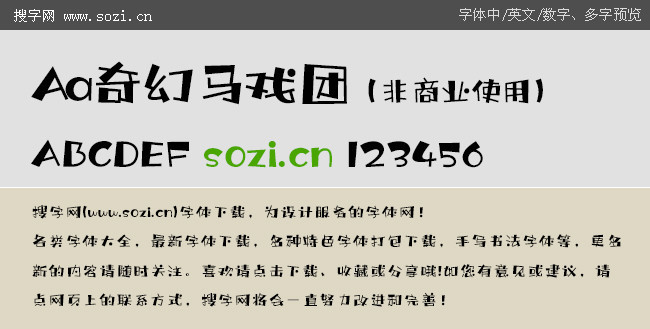
Aa奇幻馬戲團
搜字網(wǎng)給大家提供一款Aa奇幻馬戲團(非商業(yè)使用)中文字體下載,該字體是一款非常個性的藝術字體,字體形狀充滿變化,帶有濃濃的卡通風格,趣味性十足。適用于平面宣傳設計、網(wǎng)頁設計、海報設計等應用(此字體為個人非商用版,商用可以聯(lián)系QQ:1006760504)。